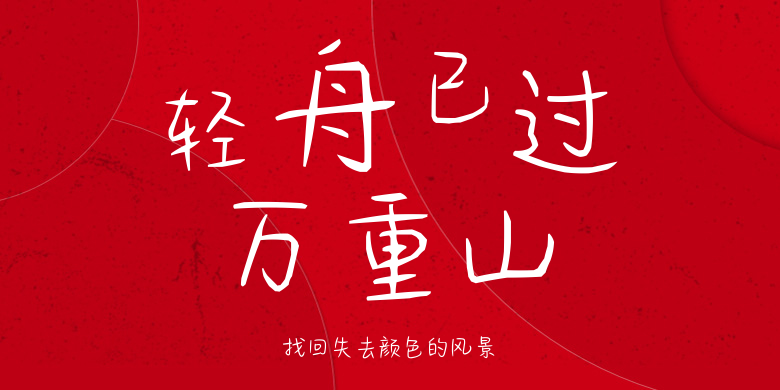
找回失去颜色的风景
找回失去颜色的风景,这款字体结构工整、笔画清晰,兼顾美观与易读性,适用于标题、正文、海报、包装、LOGO 等多种场景。字形优雅稳定,风格百搭耐看,适配日常排版与创意设计,让文字呈现更舒适、更具质感。找回失去颜色的风景一笔一画,皆是细节,以均衡的比例、流畅的线条打造舒适视觉体验,字形端正大气,风格简约现代。无论是商业设计、品牌宣传还是日常排版,都能轻松驾驭,让文字更有格调与力量。找回失去颜色的风景字体下载。